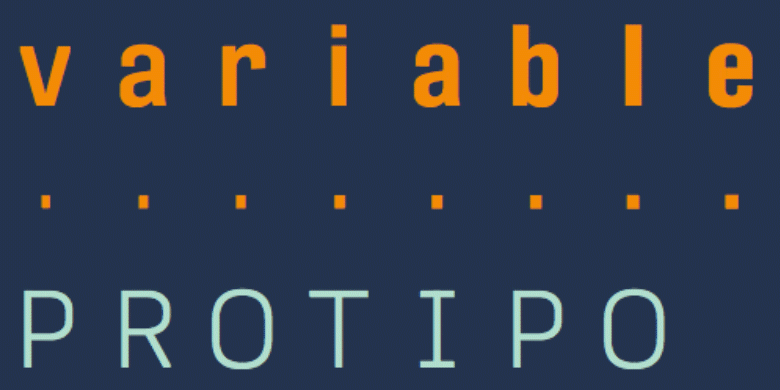
Protipo Variable可变
品牌:TypeTogether
设计师:
荷西·斯卡格里欧纳(José Scaglione),维罗妮卡·布丽安(Veronika Burian)
发行时间:2020
分类:
无衬线体
字体介绍
Veronika Burian和JoséScaglione的Protipo 字体家族是一个信息设计师的工具箱:三种字宽的低对比度无衬线字体,具有独立的标题字号家族,以及令人印象深刻的两个字重的图标集,以及可变字体(VAR)字体格式。<br><br>
从年报、导视系统到信息图表首页和海报的使用,设计师们不断地将目光转向简单明了的怪诞无衬线字体来表达他们的概念。Protipo就是基于这样的目的应运而生。<br><br>
在信息设计时,您可以从标题开始,在这个家族中,Protipo Compact用于标题字,有八个字重。从超细到特粗,把字号调大,文字重叠,或者文本溢出。Protipo Compact就是要在不同字符集和不同比例下吸引人们的注意。<br><br>
著名的信息设计师在融合形式和功能方面都是一流的,因此我们将Protipo系列与窄体风格、标准体风格和宽体风格结合在一起,作为组织信息和指导读者的一种手段。每个宽度有七个不同的字重(从细到粗)和意大利体,同时保持其DNA的圆角矩形。<br><br>
微妙的细节提升了它在文字设计领域的地位,比如在意大利体时从坚硬变为柔软的“a”和“e”,“f”有斜体的下伸部,小写的“r”和“l”有两个版本,在对角线上做切角设计,以保持这种设计作品的风格联系。
Protipo的图标设计是由Luciana Sottini根据窄体的比例制作的,之后推演到标准体和粗体。OpenType编码允许用户从数字轮廓调色板(glyph palette)中进行选择,或者只需键入其名称即可用样式集来激活它。
Protipo字体并不夸夸其谈,但是它精益求精、实用性广泛、功能强大。刚开始,变化看起来并不是明显,但Protipo家族字体不像大多数同类字体那样处理文本。Protipo字体帮助读者清晰、明确的找到和处理数据,在呈现大量信息复杂性的同时,仍然不失美学感染力。<br><br>
Protipo是所有信息环境中的理想选择:应用程序、信息图形、用户界面、导视系统、交通、海报、显示器,甚至是互联网迷因。再加上图标集和可变字体功能,你就可以保证一定程度的创造力,生产力,并影响更大的规模。